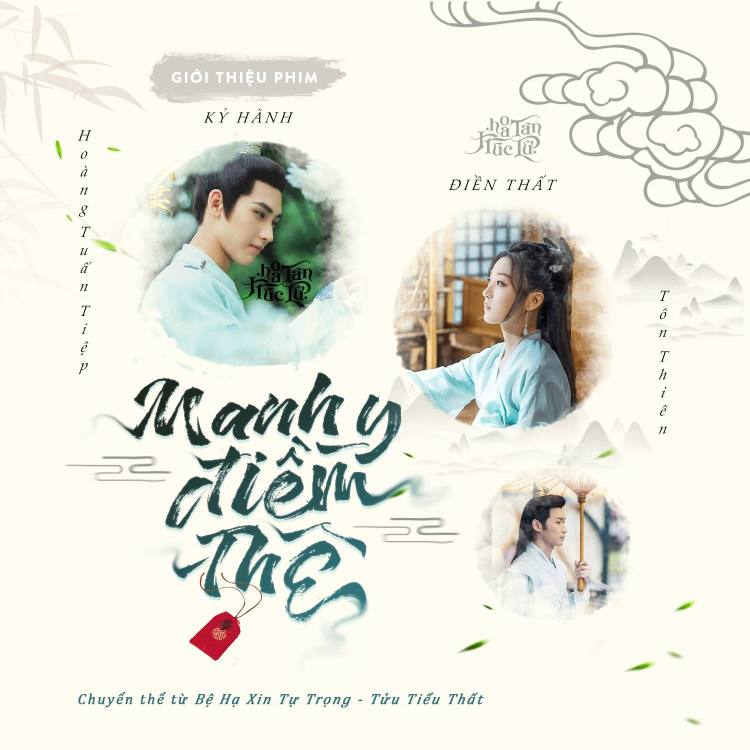
Font việt hoá MTD Addictype – Bộ font chữ thiết kế độc đáo ấn tượng
Giới thiệu về bộ Font việt hoá MTD Addictype
Trong thế giới đồ họa hiện đại, việc lựa chọn Font Chữ phù hợp đóng vai trò then chốt trong việc truyền tải thông điệp. Font việt hoá MTD Addictype là một trong những lựa chọn hàng đầu cho các nhà thiết kế yêu thích phong cách mạnh mẽ nhưng không kém phần nghệ thuật. Được trau chuốt tỉ mỉ về đường nét, bộ font này giúp các sản phẩm sáng tạo trở nên nổi bật và chuyên nghiệp hơn bao giờ hết.
Đặc điểm nổi bật của MTD Addictype
Bộ Font việt hoá MTD Addictype sở hữu các đường nét uốn lượn tinh tế cùng độ tương phản cao, tạo nên sự hài hòa cho tổng thể văn bản. Với bảng mã ký tự đầy đủ dấu tiếng Việt, người dùng có thể thoải mái ứng dụng vào nhiều dự án khác nhau từ làm poster, banner quảng cáo đến thiết kế thiệp mời hay bìa sách. Đây thực sự là một công cụ hỗ trợ đắc lực cho những ai đang tìm kiếm sự mới mẻ trong thiết kế.
Cách ứng dụng Font việt hoá MTD Addictype hiệu quả
Để tận dụng tối đa vẻ đẹp của Font việt hoá MTD Addictype, bạn nên sử dụng nó cho các tiêu đề lớn hoặc các câu trích dẫn quan trọng. Việc kết hợp font này với các tông màu tối giản sẽ làm tăng thêm vẻ sang trọng và bí ẩn cho tác phẩm. Đối với học sinh và sinh viên, đây cũng là bộ font tuyệt vời để trang trí các slide thuyết trình thêm phần sinh động và cuốn hút người xem ngay từ cái nhìn đầu tiên.
Lưu ý khi sử dụng font chữ trong thiết kế
Khi sử dụng các bộ font việt hóa, hãy đảm bảo rằng bạn đã kiểm tra kỹ các khoảng cách giữa các chữ cái (kerning) để văn bản trông cân đối nhất. Việc sử dụng Font việt hoá MTD Addictype một cách điều độ, tránh nhồi nhét quá nhiều phông chữ trong một trang sẽ giúp thiết kế của bạn giữ được sự tinh tế vốn có.
Kết luận về bộ Font việt hoá MTD Addictype